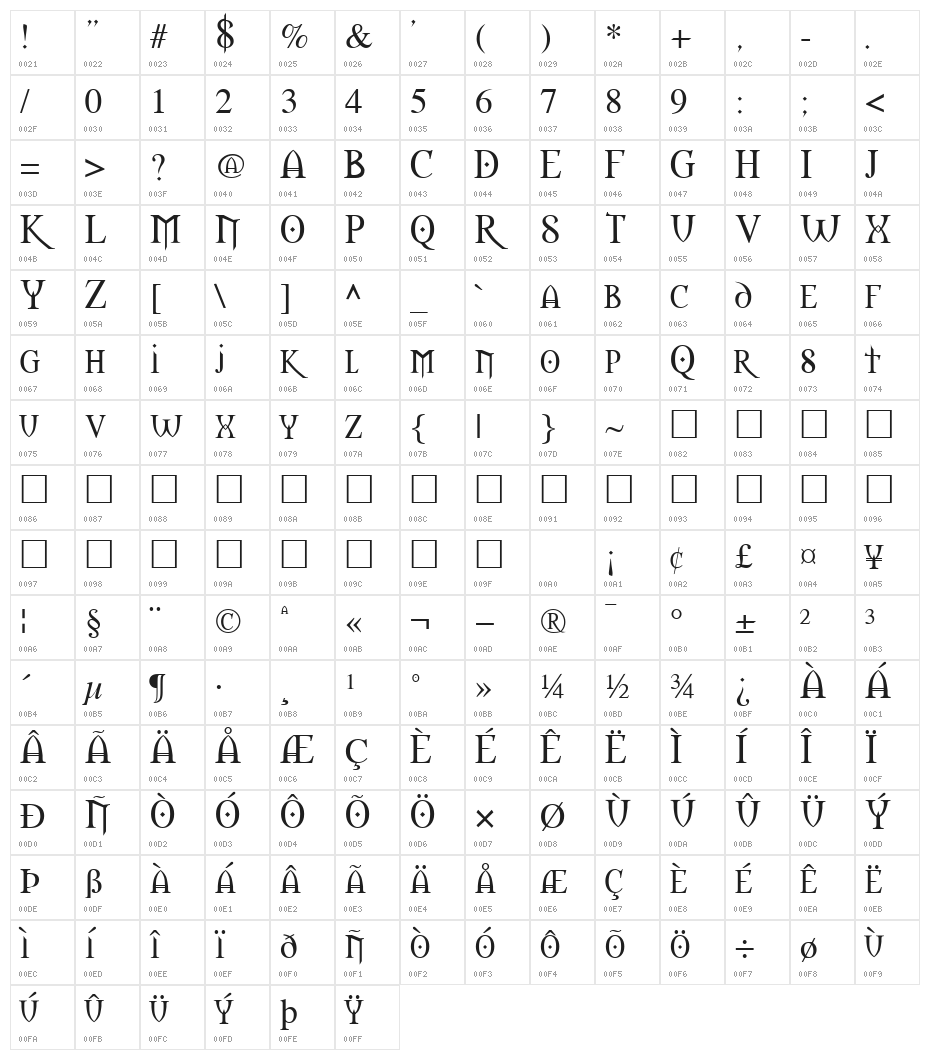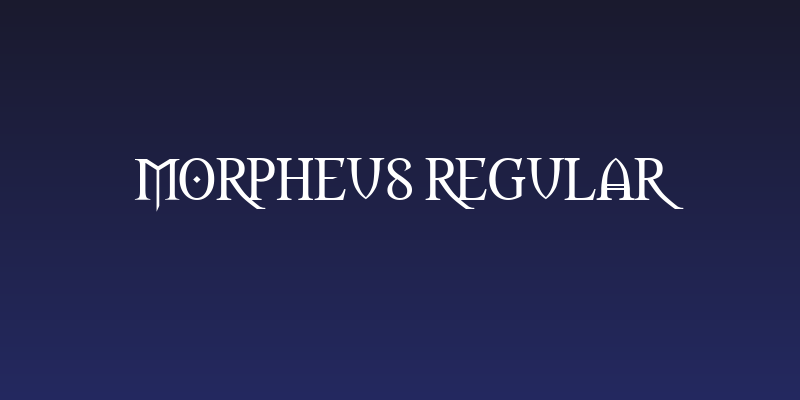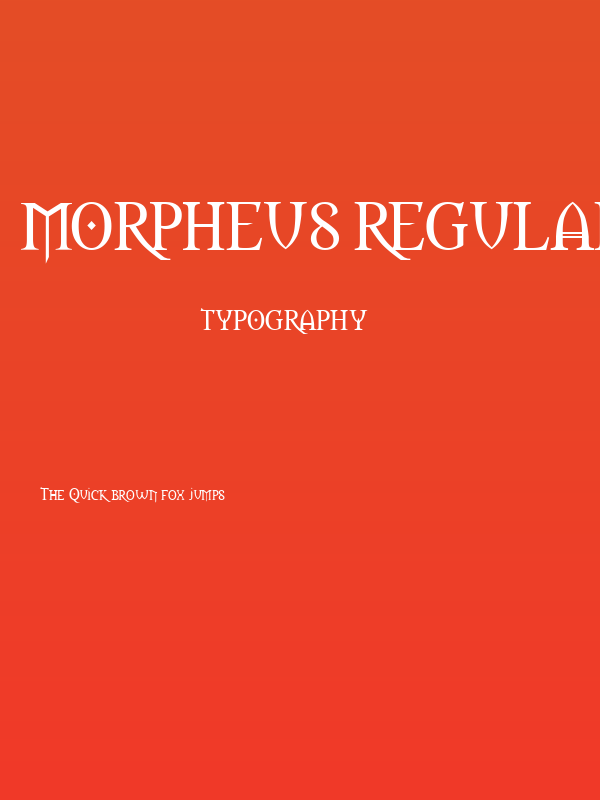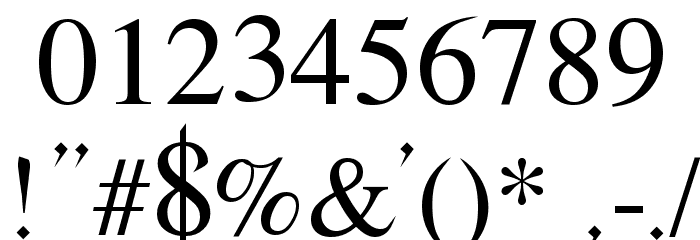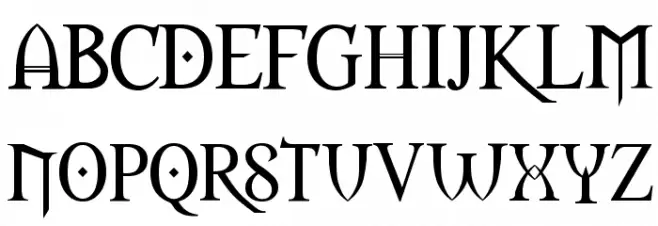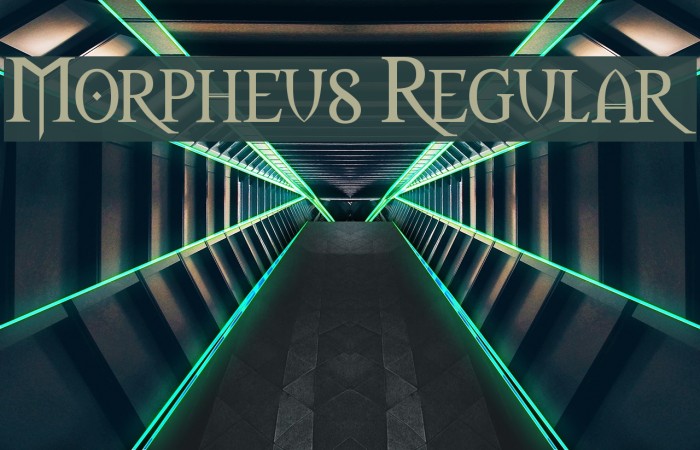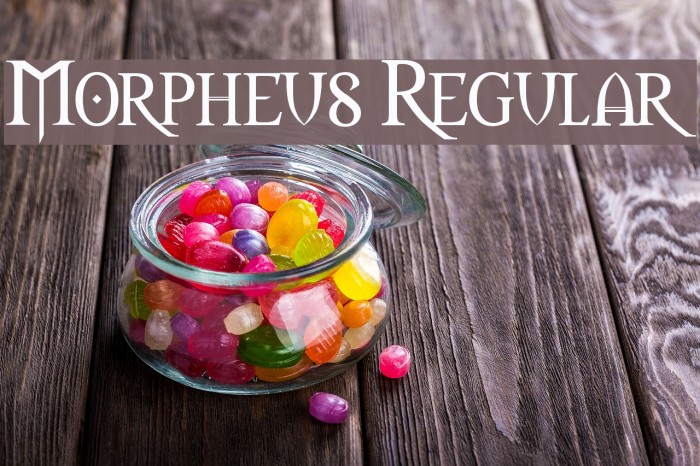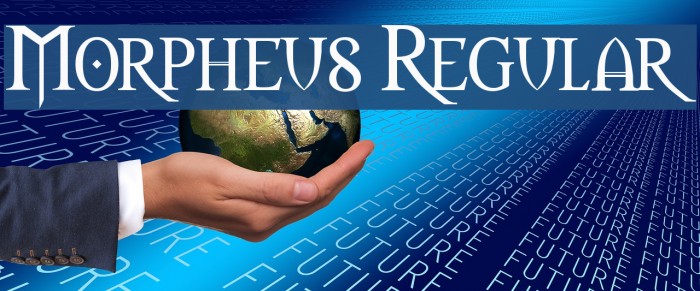
Morpheus Regular Font
| Общий стиль | Gothic, Decorative |
| Область применения | Headlines, Logos, Decorative text |
| Рекомендуемые проекты | Ideal for fantasy book covers, movie posters, themed event invitations, and branding for products with a historical or mystical theme. |